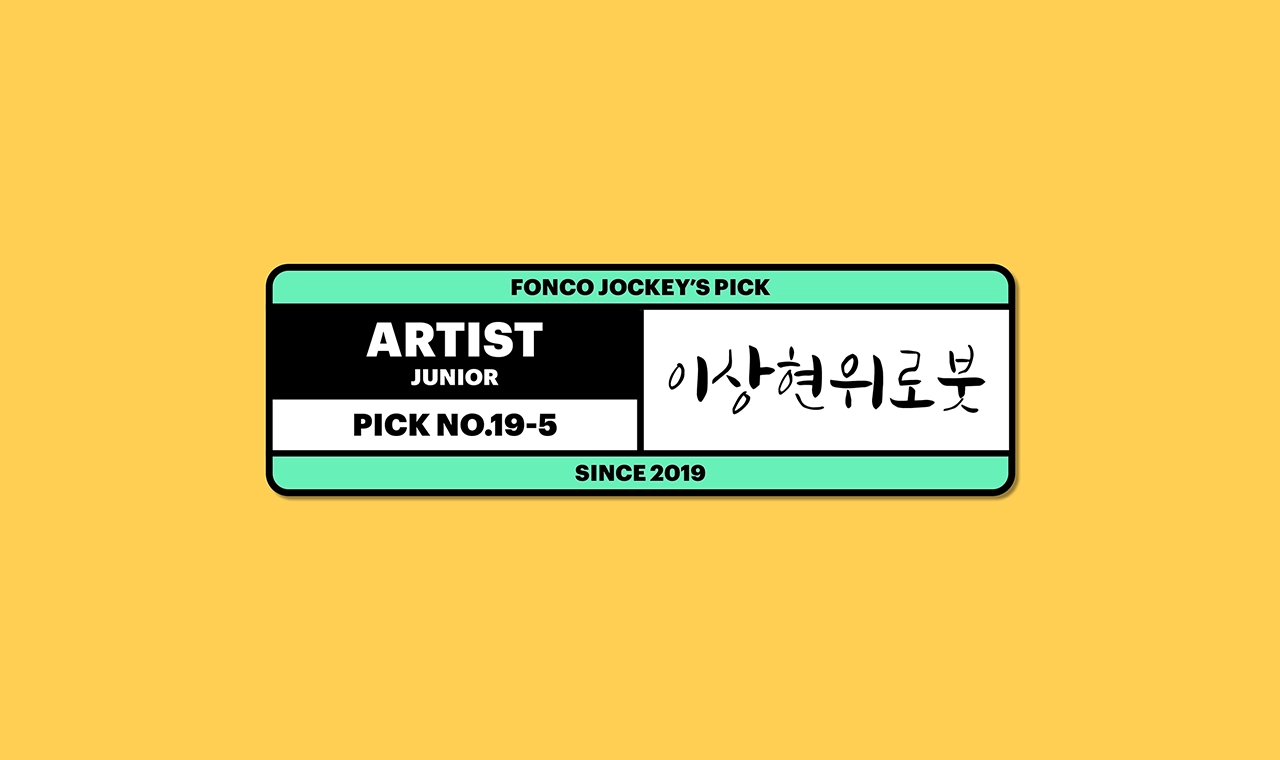
위로하는 붓, 다짐하는 펜, 캘리그래피의 맛과 멋을 한껏 느낄 수 있는 윤디자인×이상현 아티스트 폰트 콜렉션
이상현은 국내에서 캘리그래피라는 장르를 만들어낸 개척자로 평가됩니다.어린 시절 우연히 서예를 접한 뒤 대학에서도 서예학을 전공한 그는 졸업 후 마땅한 일자리가 없었음에도계속해서 글씨를 쓰고 싶었다고 합니다. 꾸준히 쓰는 삶을 살아가고 싶다는 강한 집념을 품은 채 직접 발로 뛰어서예와 디자인을 접목한 캘리그래피라는 분야를 개척하게 되었다고 합니다.
캘리그래피라는 장르를 일상으로 만들어대중과 교감하는 꿈
“제가 처음 캘리그래피를 구상할 당시, 디지털 문화의 급부상으로 전통 서예 문화는 설자리가 없었습니다.그때 저는 서예 문화의 발전을 위해 무엇을 할 수 있을까? 생각해보게 되었고 침체되어가는 전통 서예 문화를대중에게 더욱 친숙하게 알릴 방법을 궁리하게 되었습니다. 실마리가 된 것은 디자인 문화였어요.현대인의 삶은 디자인 문화 속에 놓여있더군요! 그때부터 현대 디자인 문화에 전통 서예 문화를 접목하기 시작했습니다.캘리그래피라는 장르를 일상으로 만들어 대중과 교감하는 꿈을 키우게 되었죠.그의 꿈은 생각보다 빠르게 현실이 되어갔습니다. 그가 등장하기 전인 2000년대 초반까지만 해도캘리그래피는 낯설고 생소한 분야였지만, 〈해를 품은 달〉 〈타짜〉 〈홀리데이〉 〈혈의 누〉 등 굵직한 타이틀 작업을 통해대중과 캘리그래피 사이의 간극은 점점 좁아졌습니다. 그리고 2014년 그가 뉴욕 타임스퀘어 앞에 배구장만 한흰 종이를 깔고 거대한 붓으로 아리랑을 쓰는 퍼포먼스를 했을 때, 세계인의 머릿속에 한글 캘리그래피의 인상은독보적인 존재감으로 각인되었습니다.
힘차게 쓰는 교감의 글씨
“제가 글씨를 쓰면서 가장 중요하게 생각하는 것은 교감입니다. 퍼포먼스 중에도 일방적인 압도가 아닌 주고받는 교감을 만들기 위해 관객의 반응을 예민하게 살피고 반영하지요. 소통하는 글씨를 위해서는 우리가 속해 있는 사회·문화는 물론이고 글씨 그 자체와도 끝없이 감응하며 써야 해요. 저는 그 소통이 글씨의 본질이라 생각합니다.”이처럼 이상현은 미술관에 정적으로 존재하는 글씨가 아닌 우리의 생활 곳곳에서 살아 움직이며 적극적인 소통을 만들어내는 글씨를 꿈꿉니다. 위로붓, 다짐펜으로 구성된 이상현 아티스트 폰트 콜렉션에도 역시 소통과 교감이라는 이상현의 따뜻한 메시지가 반영되어 있습니다. 누군가의 어지러운 마음을 다독이는 위로가 되어주기도, 굳센 다짐의 순간에 힘이 되어주기도 하는 글씨. 쓰는 자에게 주저 없는 격려와 용기의 말을 건네는 이상현 아티스트 폰트 콜렉션과 함께 뭉클한 교감의 시간을 체험해보시기 바랍니다.
이상현 위로붓Regular
지쳐버린 자신을 스스로 잘 다독여보자는 의미가 담긴 따스한 폰트입니다.자음, 모음 간의 획 굵기와 글자 간의 크기를 섬세하게 조정하여 토닥토닥 다독이는 운율감을 형성합니다.
이상현 다짐펜Regular
다짐이 필요한 순간에 격려를 더하는 폰트입니다.강인한 필력과 생생한 운동감이 나만의 다짐에 용기와 힘을 가득히 실어줄 거예요.